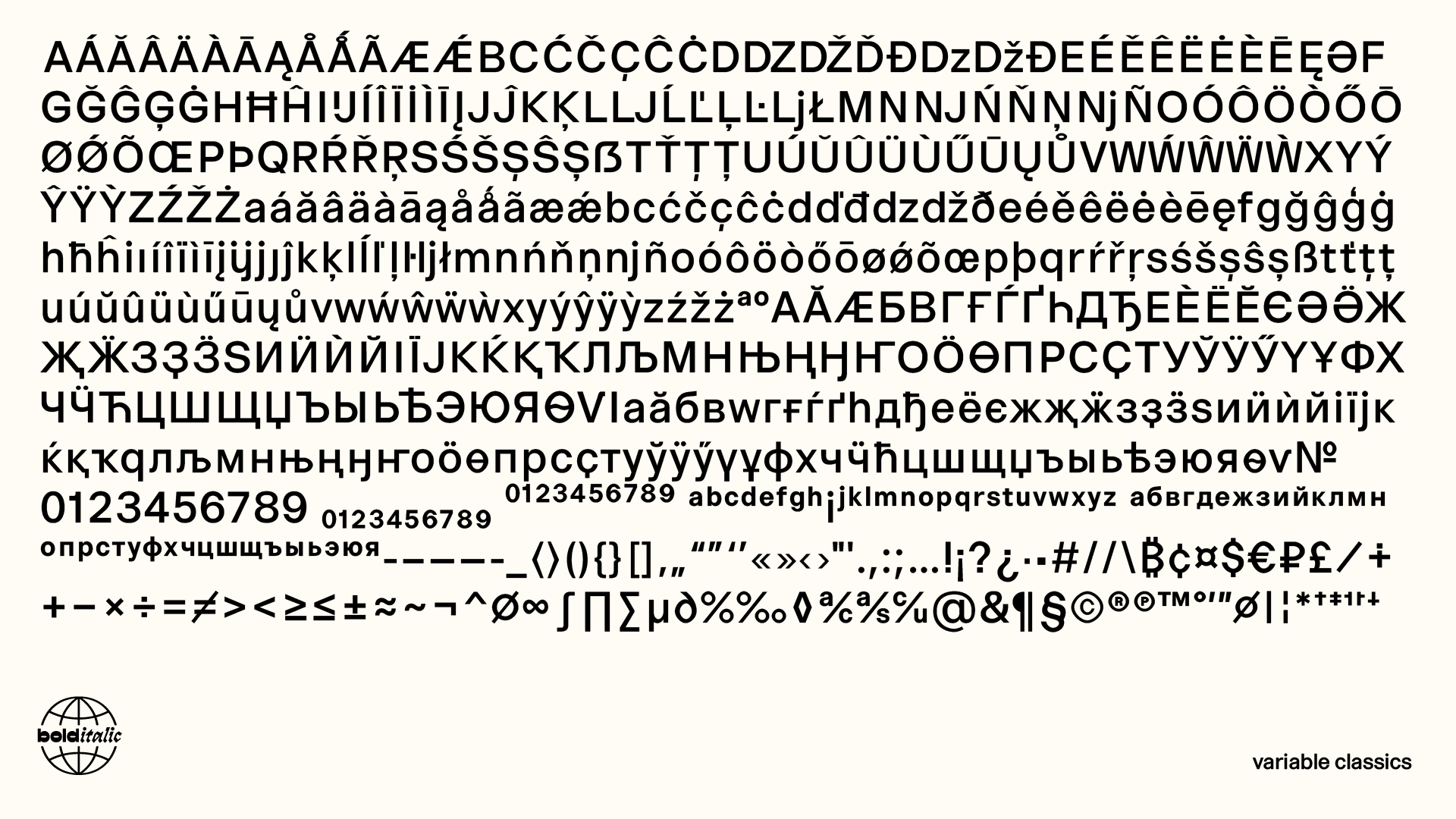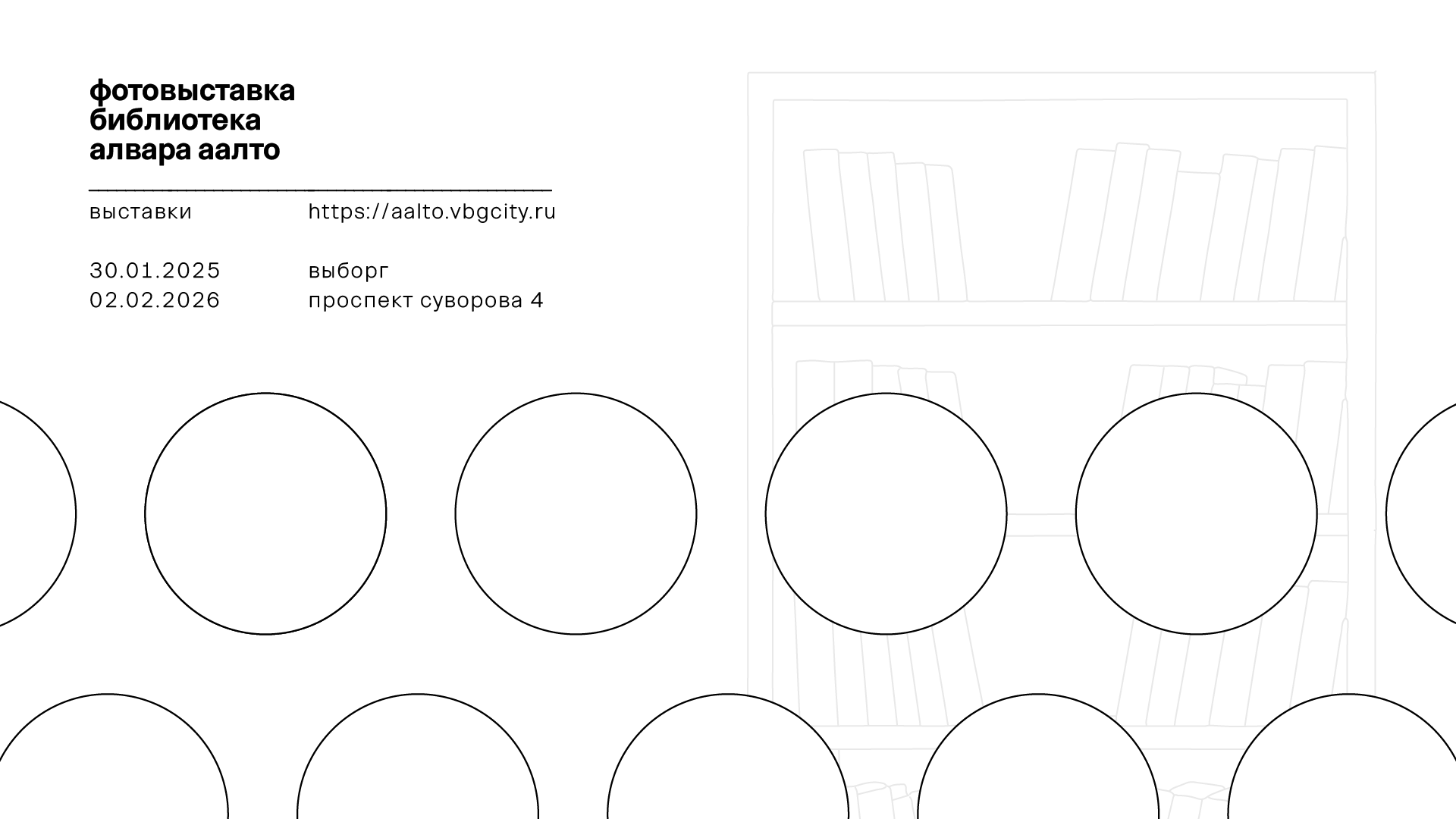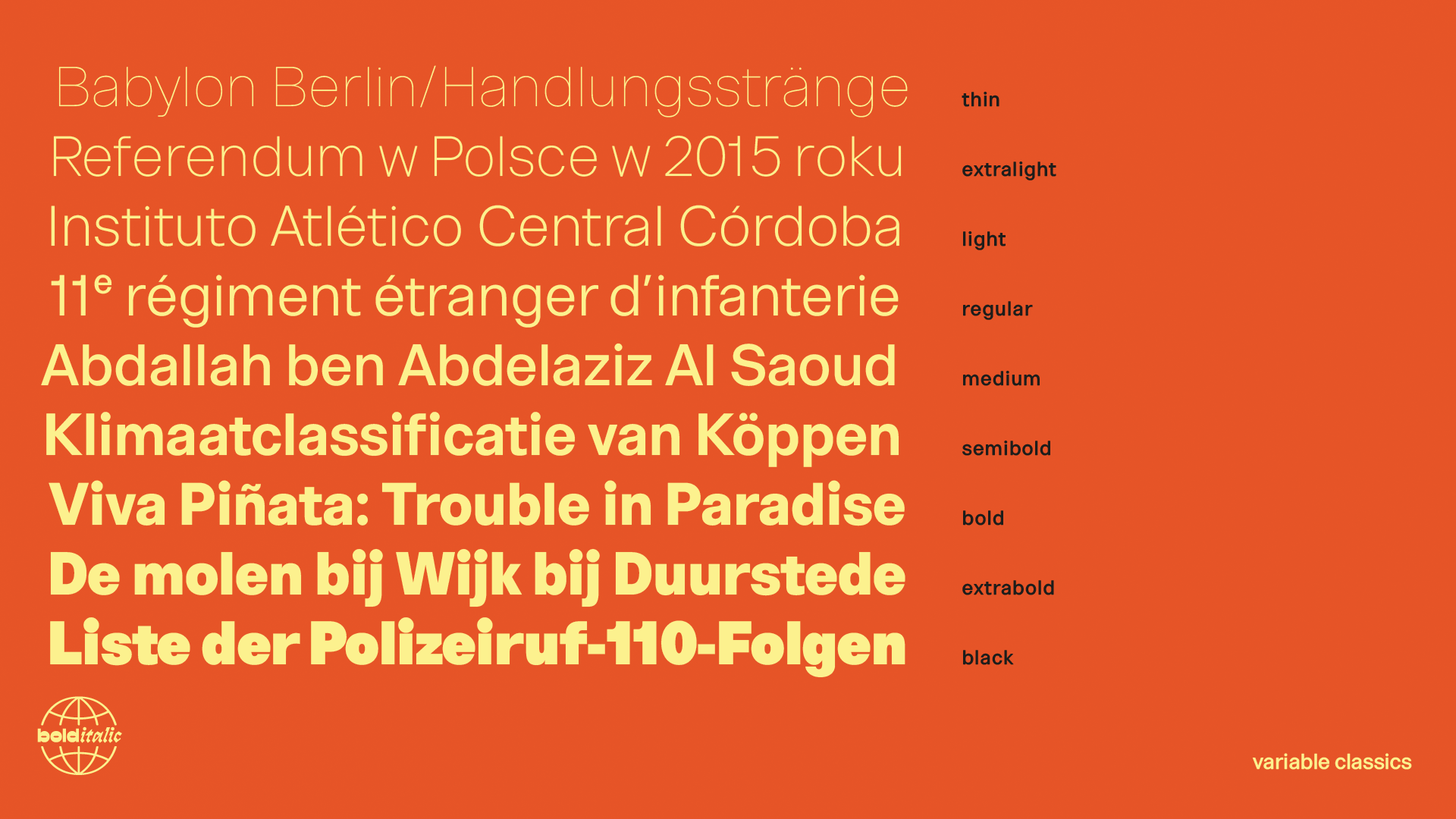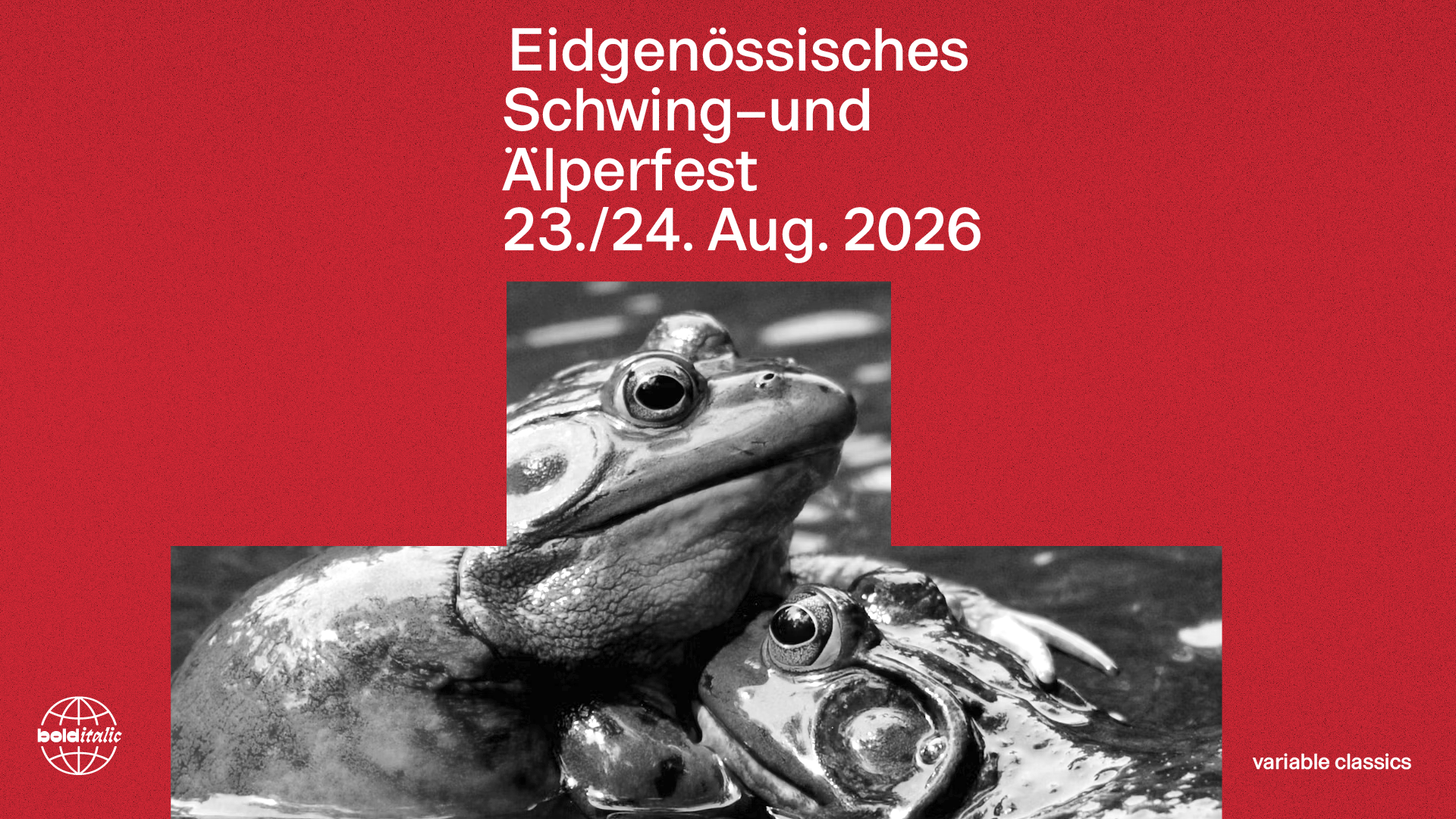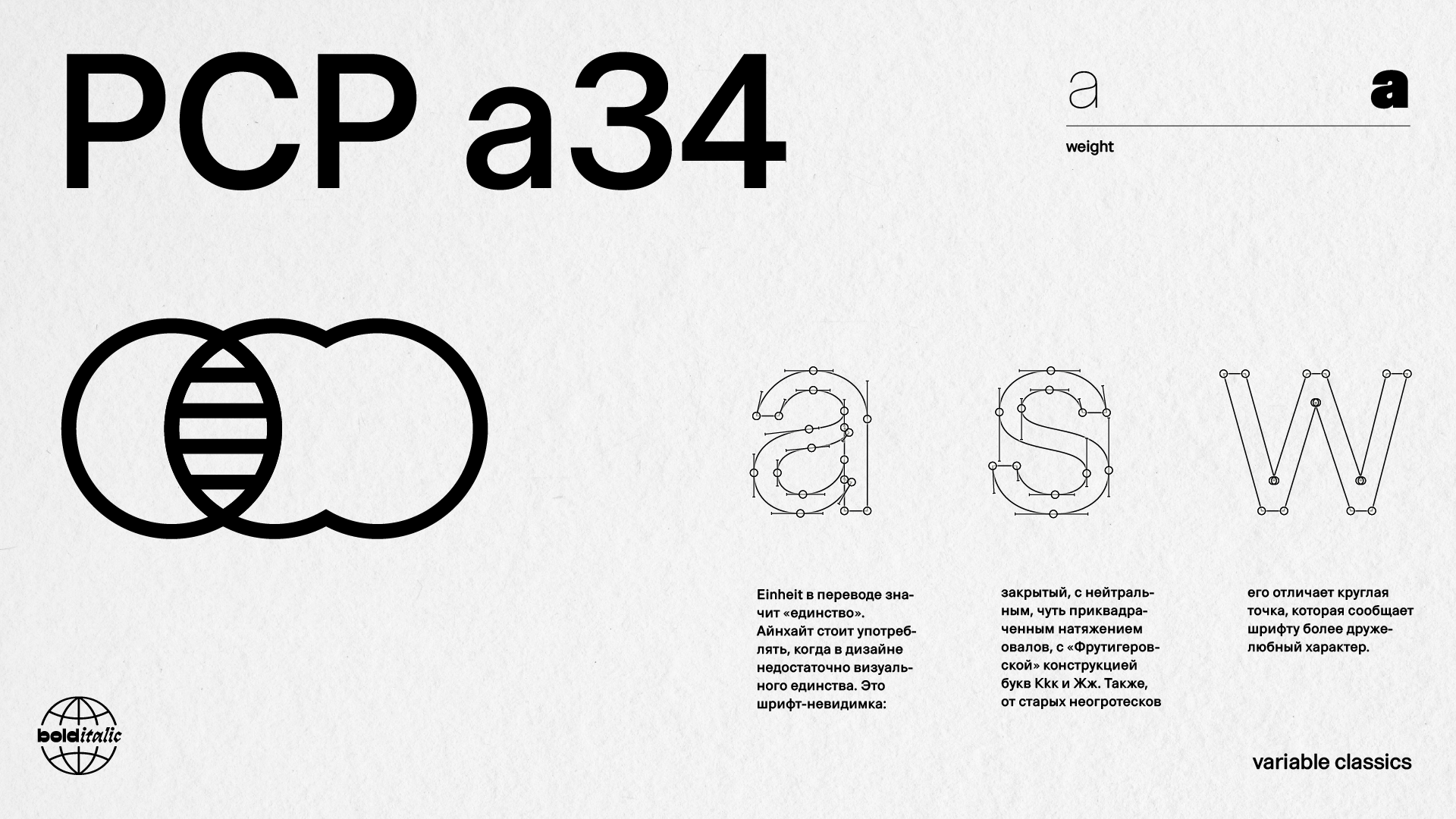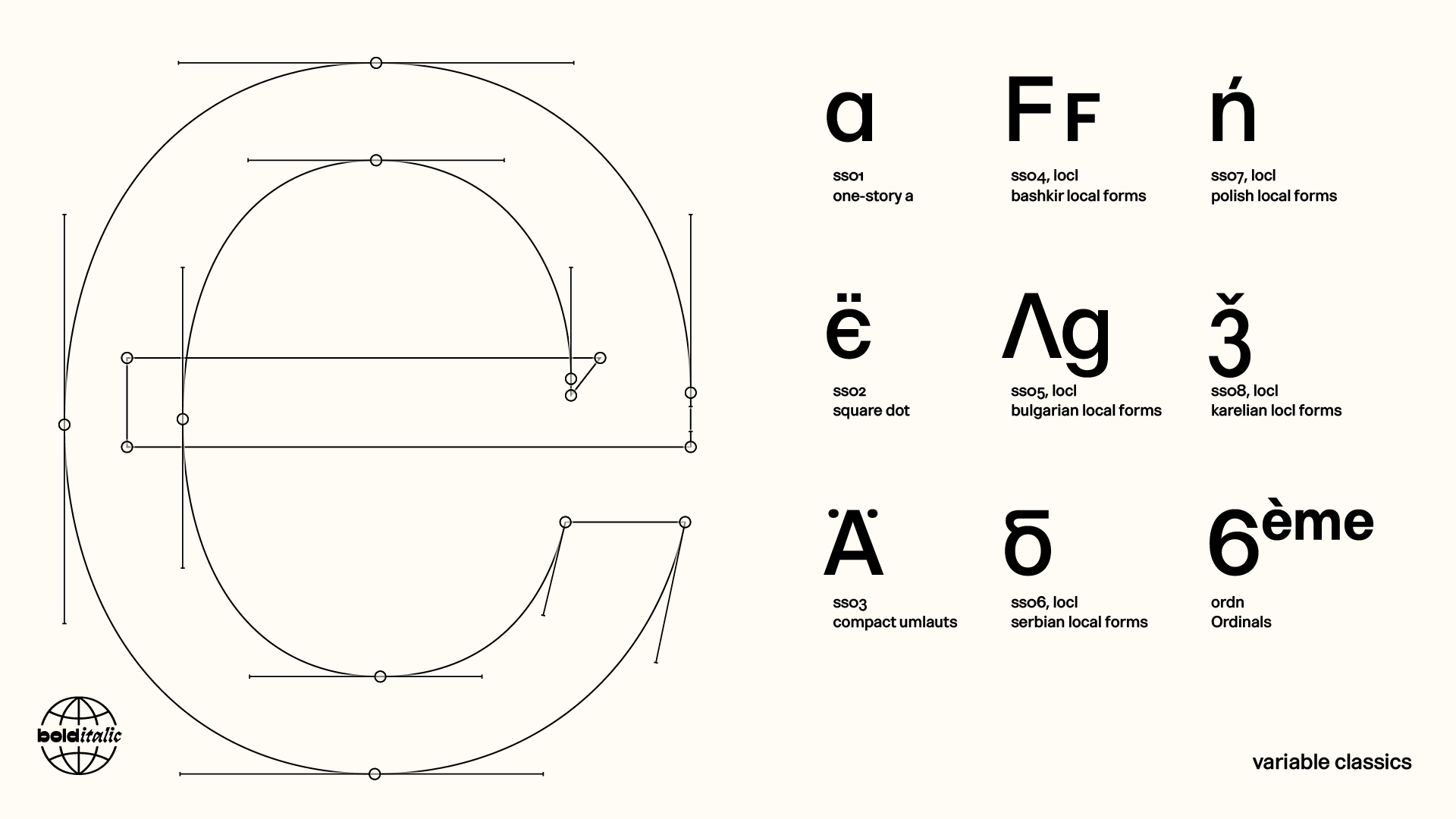
Тиражный шрифт
Einheit Grotesk
Einheit в переводе значит «единство». Айнхайт стоит употреблять, когда визуального единства в дизайне недостаточно.
На момент создания — это шрифт-невидимка: закрытый, с нейтральным, чуть приквадраченным натяжением овалов, с «Фрутигеровской» конструкцией букв Kkк и Жж. Также, от старых неогротесков его отличает круглая точка, которая сообщает шрифту более дружелюбный характер.
Студия Болдиталик